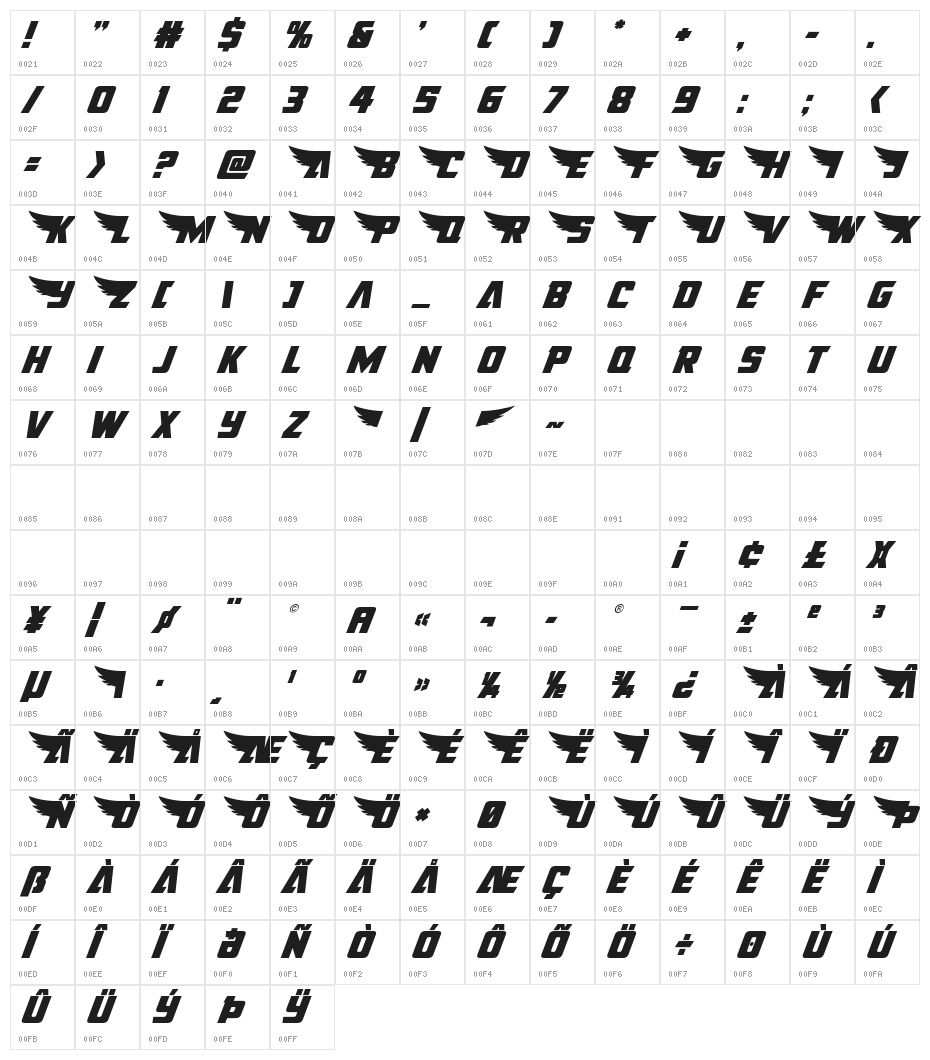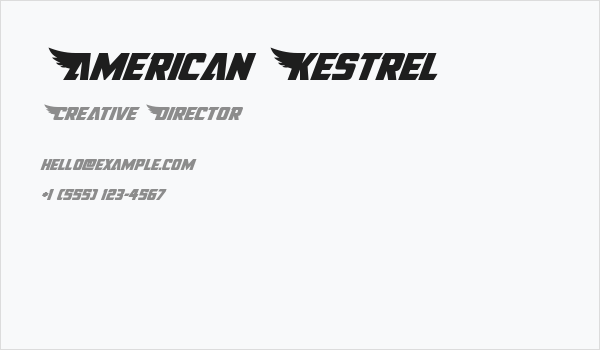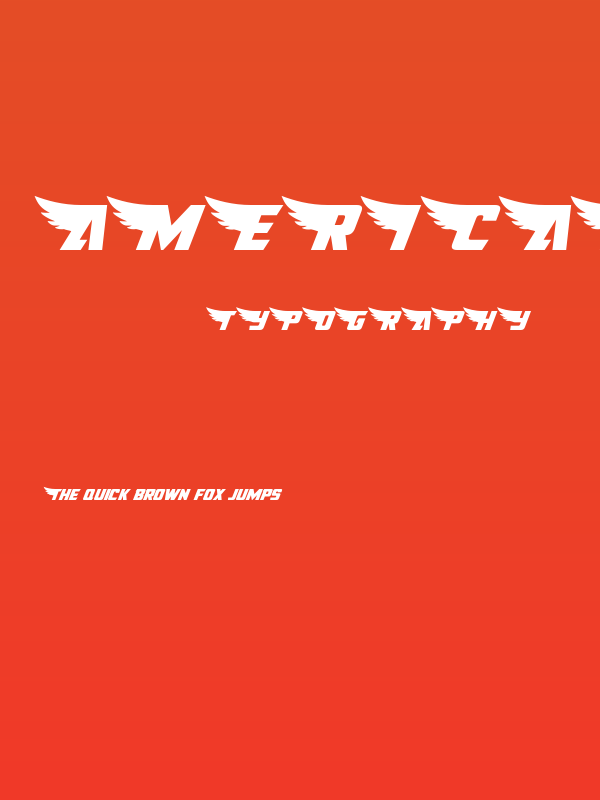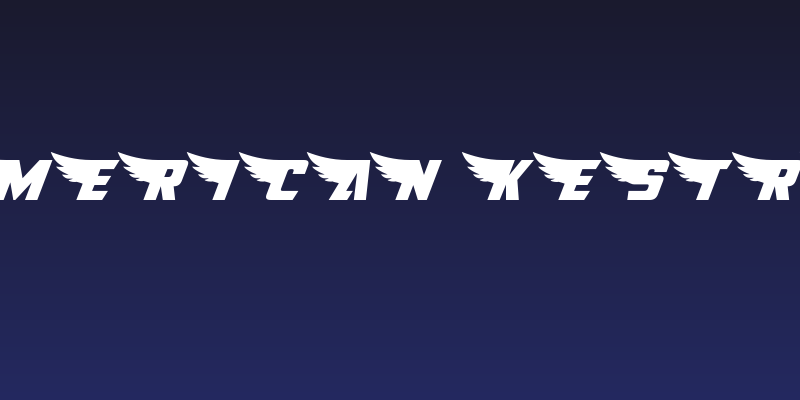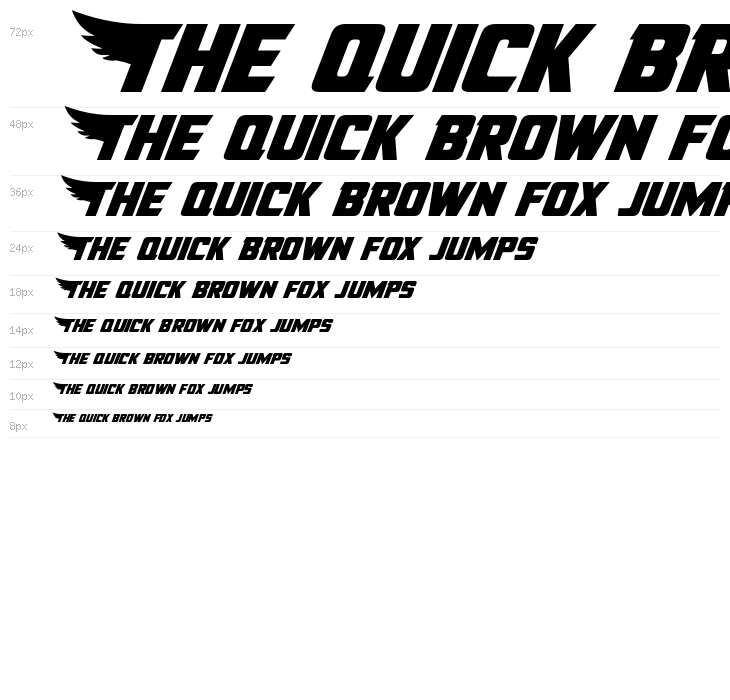
American Kestrel Font
| 使用场景 | Logos, Headlines, Posters |
| 推荐项目 | Ideal for sports branding, automotive logos, dynamic posters, and energetic advertising campaigns. |